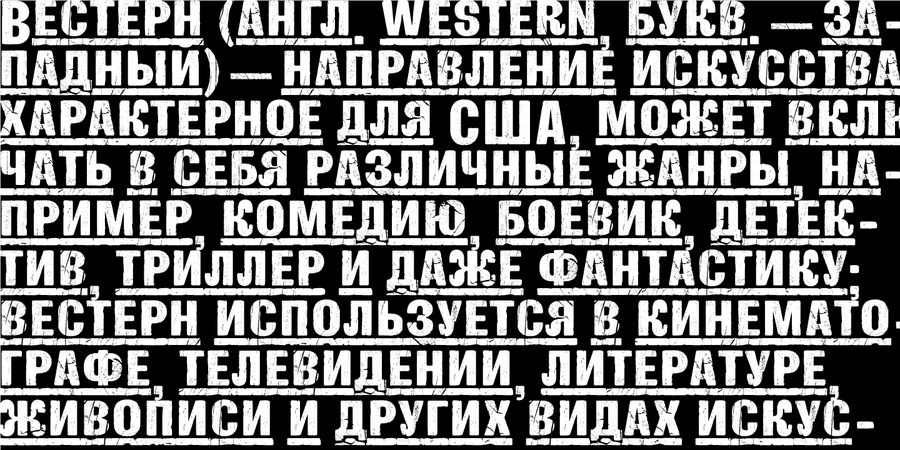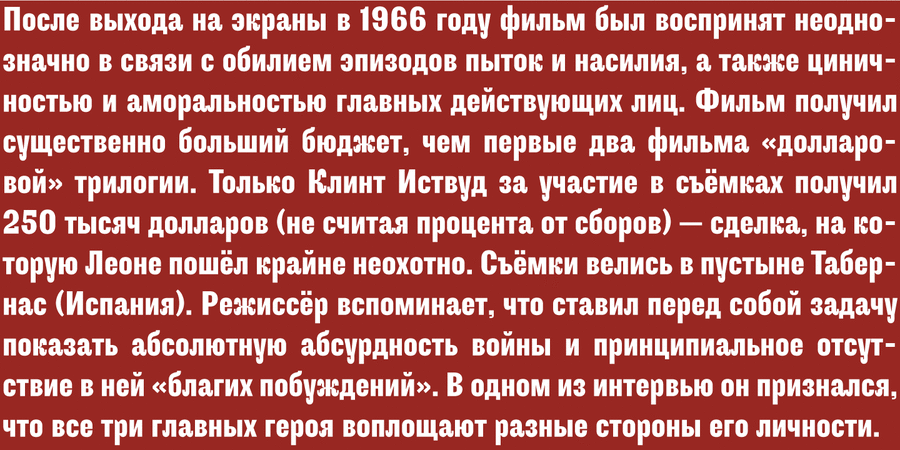
GoodBadUgly – це гротеск у стилі Дикого Заходу. Це сімейство шрифтів буде відмінним рішенням для журнальних заголовків, плакатів, вивісок, упаковки, логотипів. Шрифт розробив Кирило Ткачов в 2013 році.
Асоціації з сімейством шрифтів GoodBadUglyОсобистість і характер гарнітури:
важливий, гучний, мотивуючий, амбітний, рівний, статичний, помітний, іронічний, солідний, старомодний, стійкий, стабільний, важкий, переконливий, авторитетний, твердий, якісний, ремісничий, працьовитий, надійний, консервативний, побутовий, гангстерський, блатний, крафтовий, вінтажний, грубий, яскравий, добротний, міцний, дерев'яний, ностальгічний, робочий, різкий, чіткий, брутальний, кондовий, оригінальний, характерний, сильний, тісний, мужній, мачо, ковбойський, активний, жорсткий, суворий, самобутній, дивний, цікавий, химерний, бандитський, вуличний, високий, пивний, ветхий, старий, осінній, гарячий, вогняний, артізанальний, вернакулярний, лісовий, запальний
мафія, карти, торгівля, продукти, запас, склад, консерви, посилка, вантаж, ящик, ремесло, коваль, м'ясо, ремонт, вечеря, гамбургер, казино, тесля, деревина, ярмарок, закуска, їжа, крамниця, фермер, шахта, шахтар, вагон, джинси, взуття, салун, ковбой, ранчо, трактир, кіно, револьвер, віскі, обід, гра, техніка, інструмент, авто, залізниця, паровоз, бик, кінь, кінотеатр, цигарки, сигари, кава, пиво, осінь, паб, дерево Гарнітура має ознаки стилів: